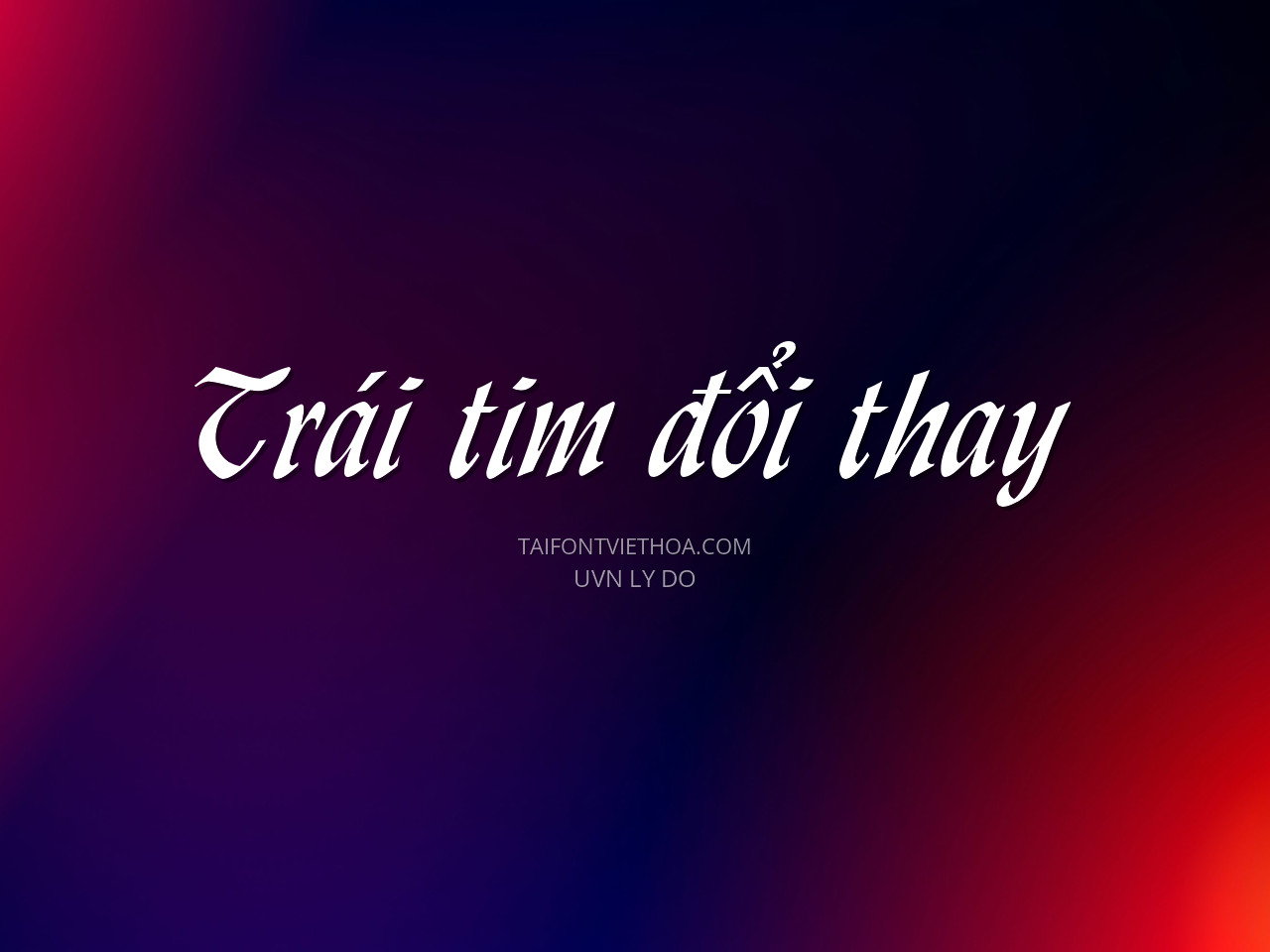
Giới thiệu về font UVN Ly Do
UVN Ly Do là một font chữ độc đáo mang hơi hướng tình cảm và trầm lắng, gợi nhắc đến những lý do cảm xúc, những dòng suy tư trong nhật ký hoặc thơ ca. Font được thiết kế với phong cách nhẹ nhàng nhưng vẫn rõ ràng và truyền cảm, phù hợp với những nội dung kể chuyện, viết tay, hoặc truyền tải thông điệp cảm xúc. UVN Ly Do được sưu tầm và chia sẻ bởi thành viên Font Chuẩn, đồng thời được taifontviethoa.com chọn lọc, ứng dụng hiệu quả trong các dự án blog cá nhân, poster truyền cảm hứng, thiệp mời và ấn phẩm mang tính cá nhân hóa.
Đặc điểm thiết kế và ứng dụng của UVN Ly Do
Font UVN Ly Do mang phong cách handwritten với các nét chữ mảnh mai, nghiêng nhẹ và mềm mại. Các ký tự được thiết kế với khoảng cách đều, tạo cảm giác nhẹ nhàng, gần gũi và chân thực. Nhờ hỗ trợ tiếng Việt đầy đủ, font dễ dàng được áp dụng trên cả nền in ấn và nền tảng số. UVN Ly Do lý tưởng cho các thiết kế cần truyền tải thông điệp cảm xúc hoặc mang yếu tố văn chương cá nhân.
Ứng dụng lý tưởng: bìa sách, blog tâm sự, thiết kế thiệp, bài thơ, trang nhật ký, sản phẩm sáng tạo cá nhân. Ngành nghề phù hợp: truyền thông cảm xúc, xuất bản, giáo dục, thiết kế thiệp cưới và nghệ thuật handmade.